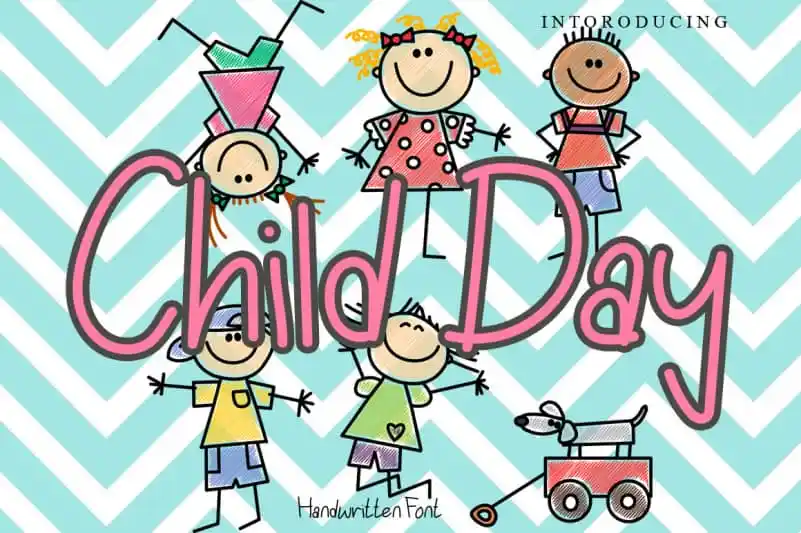
A ‘Child Day Display Font’ é uma elegante escolha para aqueles que buscam um estilo descontraído e fresco, inspirado em pintura à mão livre. Este tipo de fonte oferece a característica natural e única, o que a torna perfeitamente adaptável a uma ampla gama de projetos. A serenidade e leveza deste design fazem dele não apenas um recurso visual elegante para seus designs, mas também uma ferramenta divertida para explorar inúmeras variações únicas. Esta fonte é ideal para designers que querem trazer alegria e descontração ao seu trabalho, ou simplesmente aquelas pessoas que adoram jogar com as letras de vez em quando. Experimente esta ‘Child Day Display Font’ e descubra como ela pode transformar seus projetos no espaço do design.